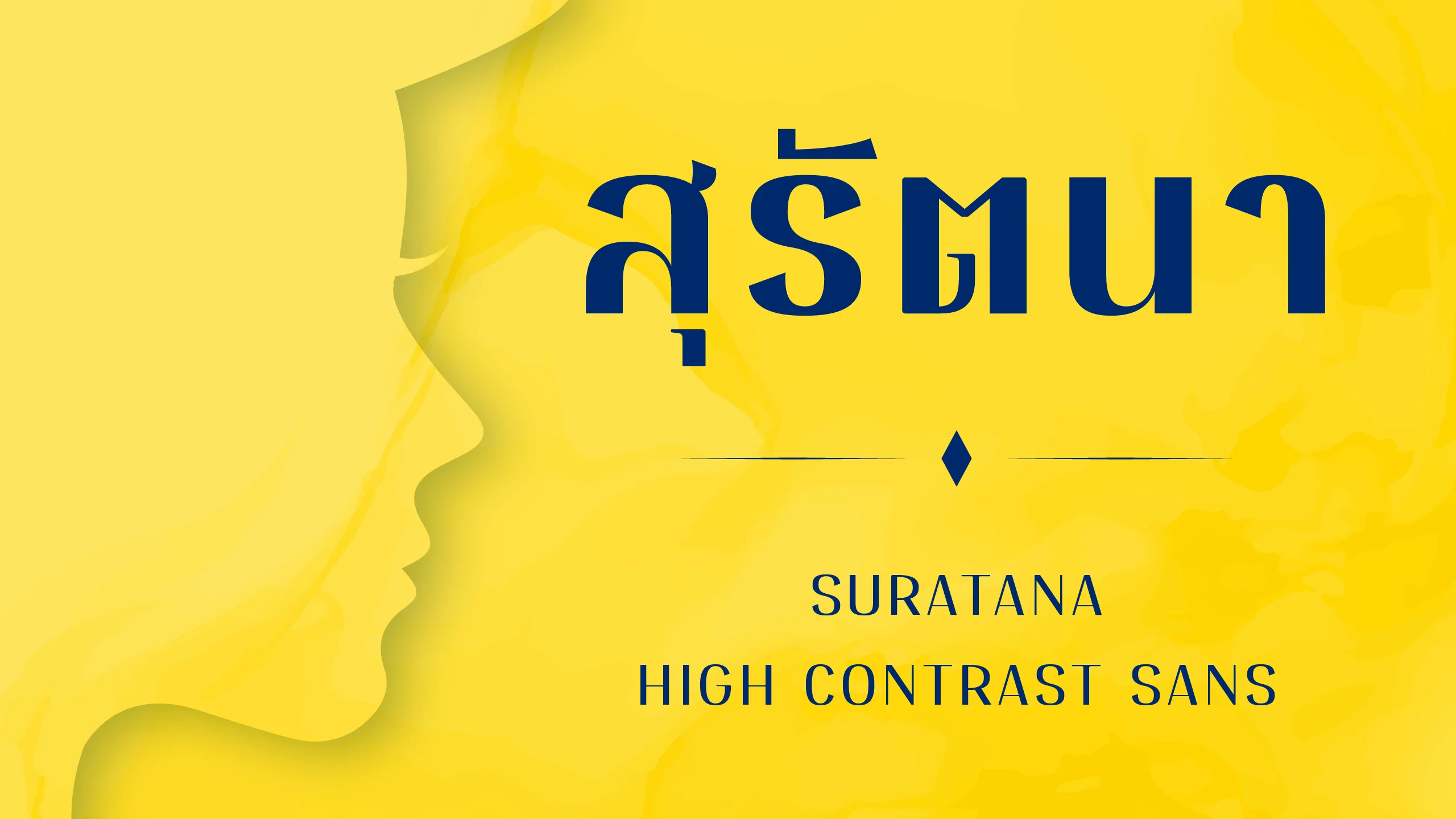
SURATANA SANS
"สุรัตนา แซนส | SURATANA SANS" คือชุดอักษรที่นำโครงสร้างอันแข็งแกร่งและสมดุลของตระกูล "สุรัตนา" มานำเสนอในรูปแบบ High Contrast Sans ที่ตัดทอนส่วนเกินออกจนเหลือเพียงความเรียบง่ายที่ทันสมัย มอบบุคลิกที่ดูสะอาดตา มั่นคง และเป็นสากลมากขึ้น แม้จะเป็นฝาแฝดที่มีโครงสร้างร่วมกัน แต่สุรัตนา แซนส์ กลับมอบความรู้สึกที่แตกต่างด้วยความโฉบเฉี่ยวและเป็นมิตร เหมาะสำหรับโลกการสื่อสารยุคใหม่ที่ต้องการความชัดเจนและเรียบง่ายเป็นหัวใจสำคัญ ด้วยรูปลักษณ์ที่ดูโปร่งสบายและมีความสม่ำเสมอ "สุรัตนา แซนส | SURATANA SANS" จึงตอบโจทย์งานออกแบบที่เน้นความร่วมสมัยได้อย่างหลากหลาย ตั้งแต่งาน UI/UX บนสื่อดิจิทัล ไปจนถึงการจัดวางพาดหัวที่ต้องการความโมเดิร์นและดูเป็นระเบียบ การเลือกใช้ฟอนต์ชุดนี้ในงานดีไซน์จะช่วยให้ข้อมูลดูเข้าถึงง่ายและดูเป็นมืออาชีพ พร้อมสร้างสมดุลที่ลงตัวเมื่อใช้งานร่วมกับชุดอักษรสุรัตนา (แบบ Serif) เพื่อสร้างมิติการสื่อสารที่น่าสนใจและมีชั้นเชิงยิ่งขึ้น เพิ่มมิติความหรูหราให้กับงานออกแบบของคุณด้วยคู่แฝดสไตล์ Serif อย่าง "สุรัตนา | SURATANA" ที่ใช้โครงสร้างตัวอักษรเดียวกันแต่แฝงไว้ด้วยความภูมิฐานและคลาสสิก เหมาะสำหรับใช้ควบคู่กันเพื่อสร้าง "สำเนียง" การสื่อสารที่น่าจดจำและทรงคุณค่า